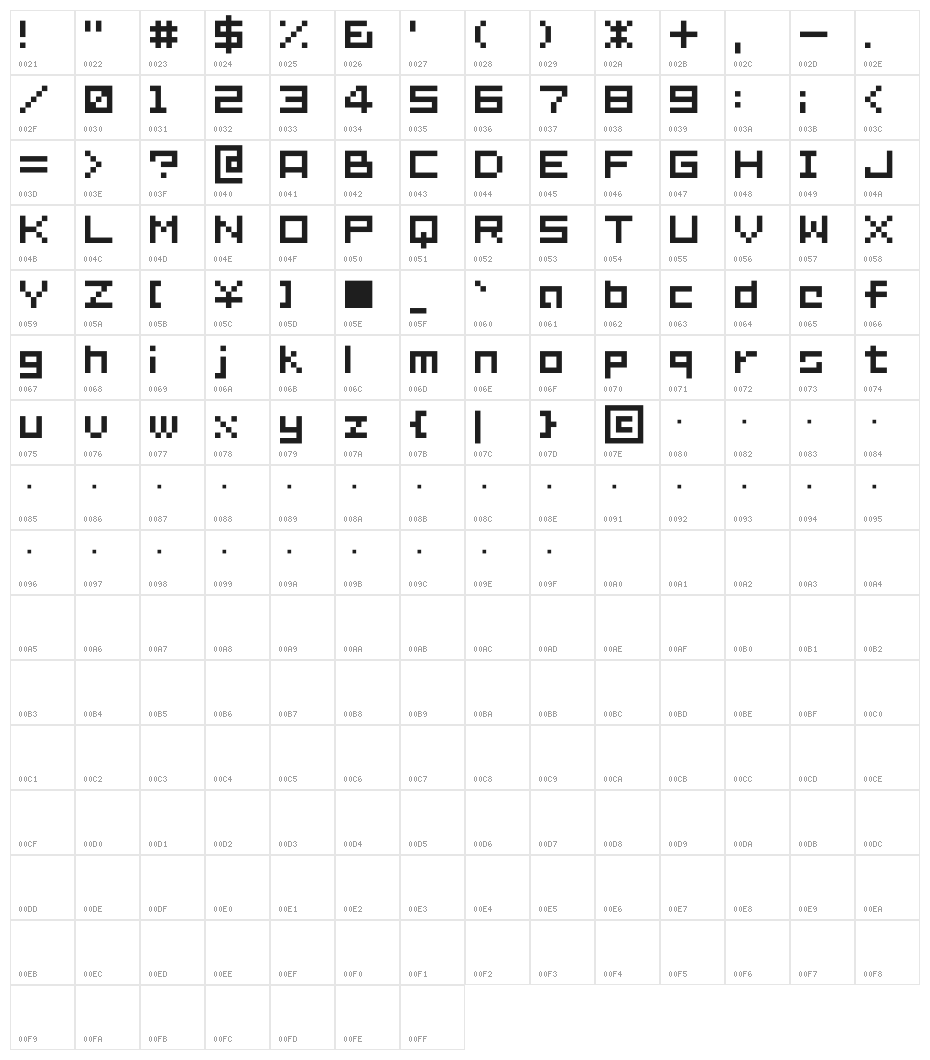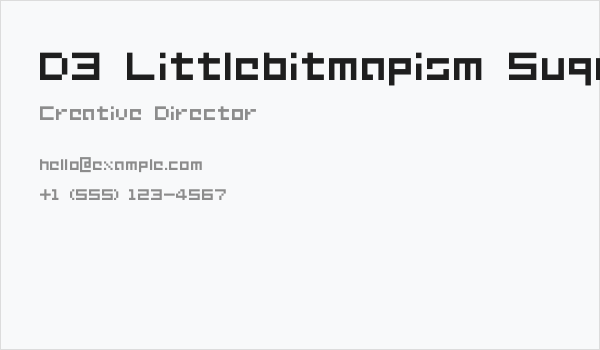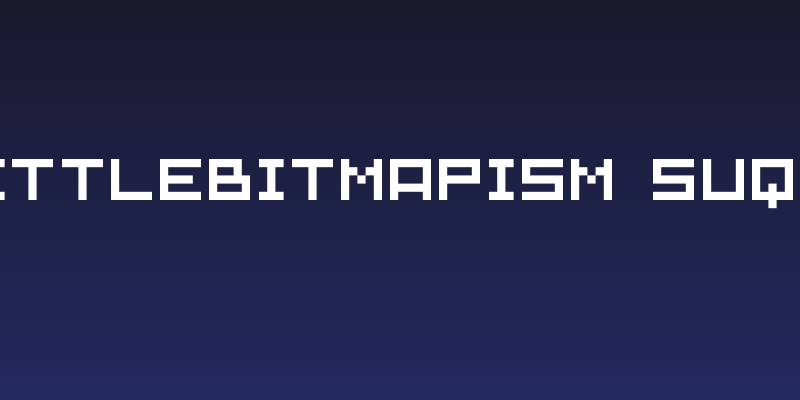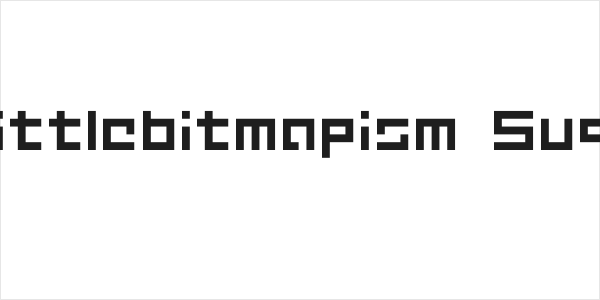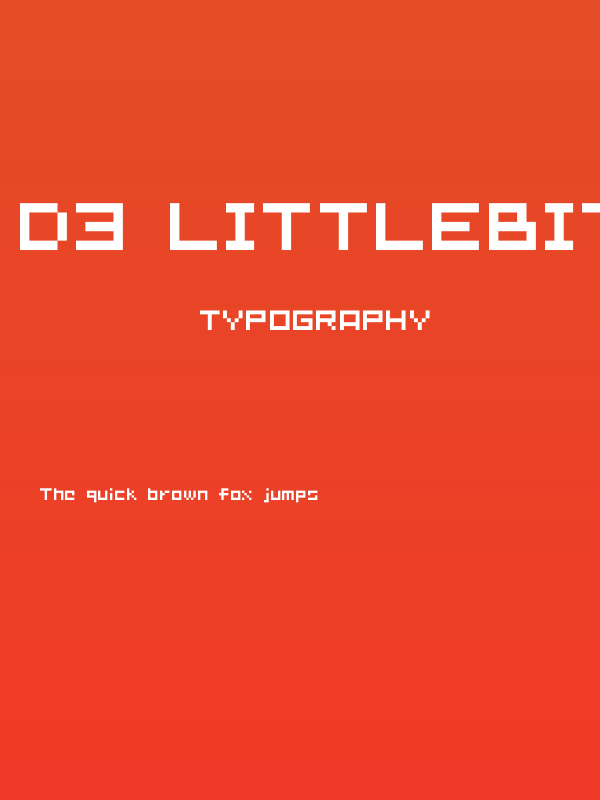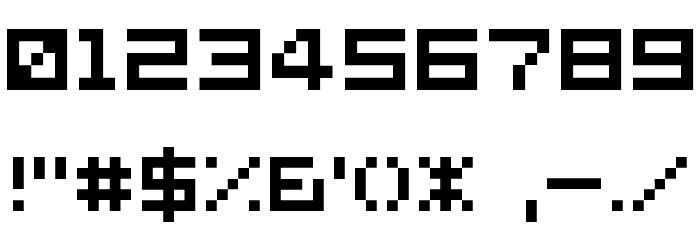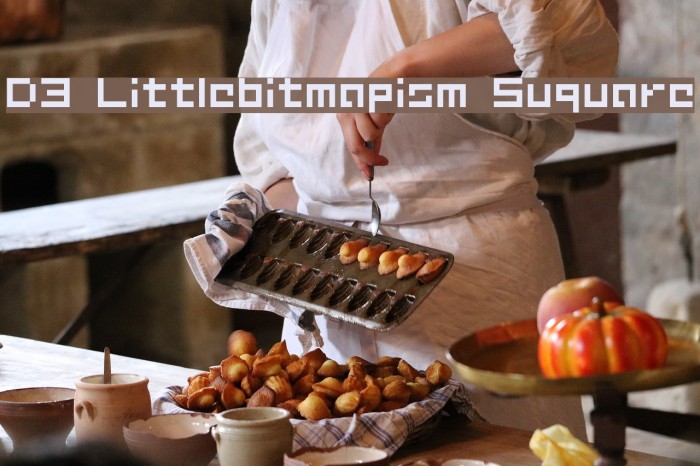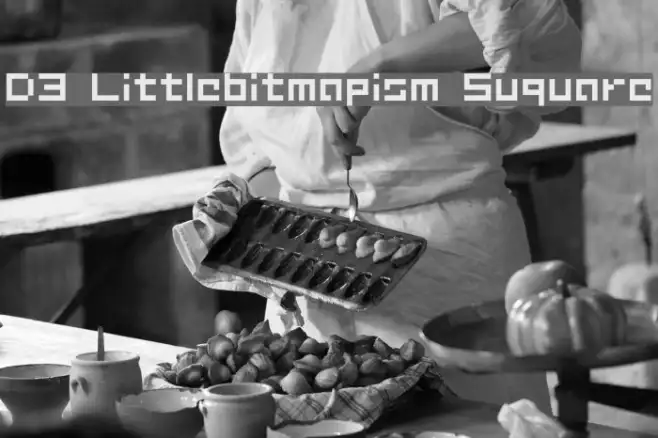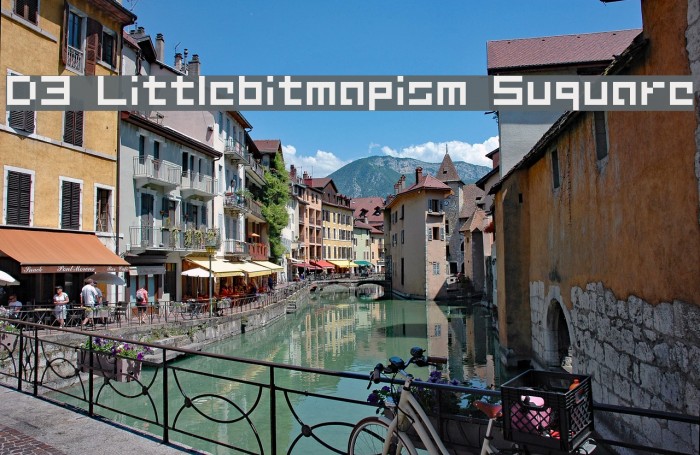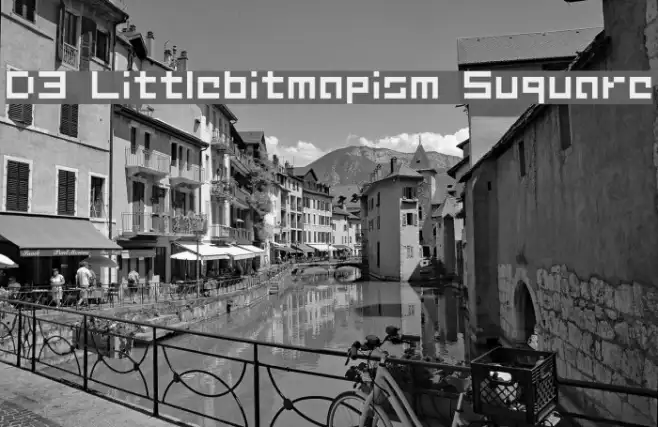
D3 Littlebitmapism Suquare Font
| Cas d'utilisation | Logos, Headlines, Digital displays |
| Projets proposés | Ideal for retro-themed designs, video game graphics, digital art projects, and any creative work that requires a nostalgic digital touch. |